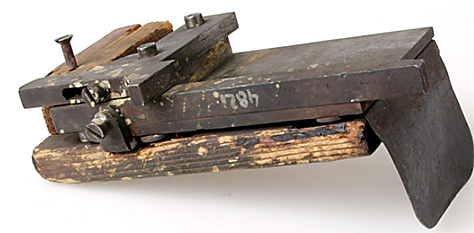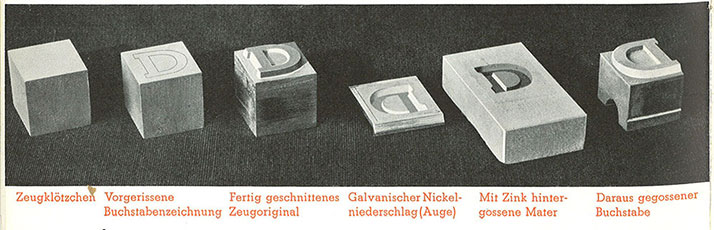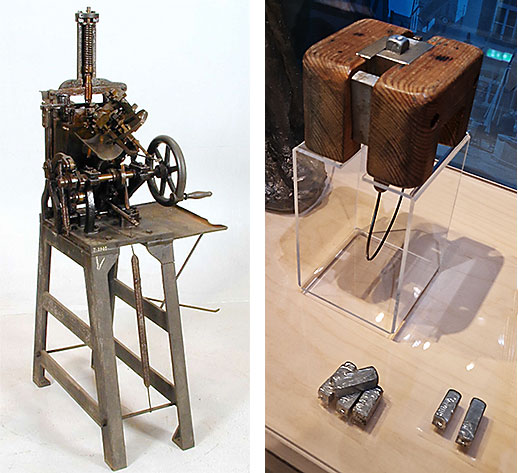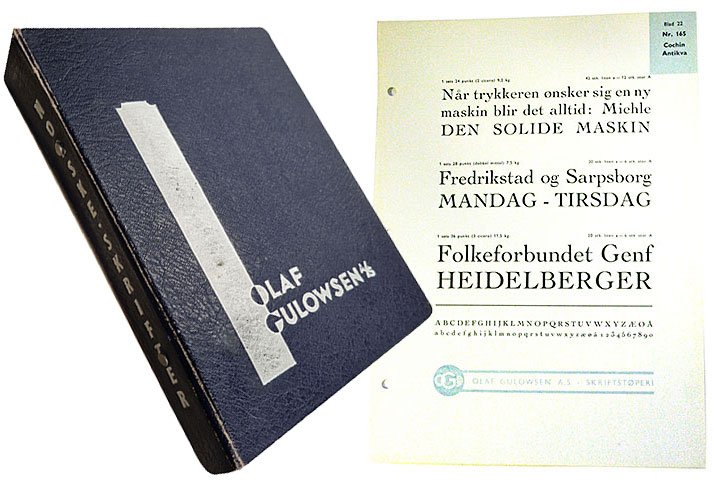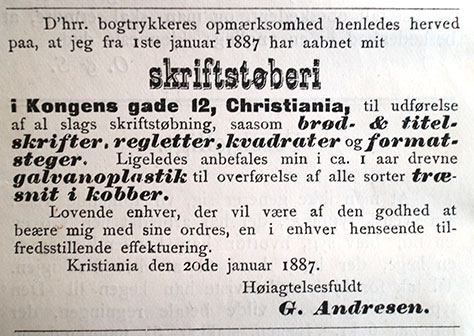
Typografer, grafiske designere og andre med kjærlighet for trykkskrift vil gjenkjenne navn som Stempel, Amsterdam, Klingspor og flere andre som hederskronte skriftstøperier. Disse forsynte norske trykkerier i en årrekke med blyskrift. Men Norge var ikke alltid helt avhengig av import av skrift til sine trykkerier.
For også Norge har en historie innen skriftstøping. Både en kjent, om enn lite omtalt historie om et middels stort norsk skriftstøperi, i tillegg til en ganske ukjent historie om flere mindre skriftstøperier, som her blir fortalt for første gang. Enkelte større trykkerier støpte dessuten noe av sin egen skrift.
Den kjente historien handler om Det norske skriftstøperi i Oslo. Bedriften støpte skrift i 30–40 år på 1900-tallet. Sortimentet var basert på lånte og kjøpte matriser fra Monotype Corporation i England. I 1960 utga firmaet ei bok i anledning sitt 25-års jubileum. Her heter det: «Det hadde til da [bedriftens oppstartsår 1934] ikke eksistert noe skriftstøperi i Norge.»
Dette stemmer ikke. Den nesten ukjente historien om norsk skriftstøping handler om hele seks andre skriftstøperier. Disse var virksomme fra slutten av 1800-tallet og et stykke inn på 1900-tallet, men har vært nær ukjente i vår tid.
Det er ingen holdepunkter for at det ble støpt originale skrifter i disse skriftstøperiene. Å formgi og produsere en original skrifttype var et stort og kostbart arbeid som forutsatte høy fagkunnskap og kunstnerisk talent, i tillegg til et større marked for skriften. Likevel er den norske skriftstøpingen en interessant flik av norsk boktrykkhistorie, som gir et glimt inn i forholdene i boktrykkerfaget da det det var i sterk vekst og tok form for 130 år siden.
Det norske skriftstøperi
Det norske skriftstøperi startet som et skriftstøperi under den grafiske utstyrsleverandøren Olaf Gulowsen A/S i 1934. Det var tilknyttet skrift- og settemaskinprodusenten Monotype i England gjennom deres nordiske sentral for skriftmatriser i Stockholm: Scandinavian Display Matrix Library, som var i virksomhet i hvert fall fram til 2. verdenskrig. I 1950 ble støperiet skilt fra moderfirmaet under eget navn, Det norske skriftstøperi, og hadde i 1960 12 ansatte. Jeg har ikke kunnet fastslå når bedriften opphørte.
I den nevnte jubileumsboka ved firmaets 25-årsjubileum i 1960, Halvor Durban-Hansens Skrift og typer, kan vi lese at uten samarbeidet med Monotype i England ville skriftstøperiet ikke vært mulig å realisere. Men det norske grafiske markedet satte pris på muligheten for omgående levering av skrift fra et innenlands støperi, når kvaliteten var god og prisene konkurransedyktige.
Utvalget av skrift fra Olaf Gulowsen/Det norske skriftstøperi var begrenset, som vist i deres skriftprøve, som av Nasjonalbiblioteket er antatt å være utgitt i 1940. Skriftene ble støpt i grader (størrelser) fra 6 til 72 punkter, men kun Bodoni dekket hele dette spennet. Så å si alle skriftene i prøven lar seg identifisere som Monotype-skrifter.
En brosjyre fra 1950-tallet viser at sortimentet var blitt utvidet noe, bl.a. med de populære bokskriftene Bembo og Goudy, mens andre skrifter var gått ut.
Skriftkatalogen til Olaf Gulowsen A/S fra ca. 1940 (ennå ikke omdøpt til Det norske skriftstøperi). Til høyre en side i katalogen, som viser den den gang populære skriften Cochin. (Ill.: Verkstedet – verkstedet.org)
Skrift og typer er både en vakker og interessant bok, som ikke er vanskelig å skaffe seg antikvarisk i dag. Den gir blant annet en innføring i historien og teknologien knyttet til skriftstøping, som er nyttig å kjenne til i det følgende.
Skriftstøpingens teknikk
Opprinnelig besto framstillingen av typer i å først gravere et såkalt stempel i stål, der bokstaven står i relieff – en såkalt patrise (far-form). Dette stemplet ble så preget inn i et annet og mykere metallstykke, slik at bokstaven sto dyptliggende i dette – en såkalt matrise (mor-form). Fra matrisen støpte man blytypene i et manuelt støpeapparat, en etter en. Før de var klare til bruk, måtte overflødig metall slipes av typene. Et dagsverk kunne resultere i 4000–5000 typer.
Til venstre: en skriftstøper i det 17. århundre, sammen med en kvinne som sliper typene. Til høyre: patrise, matrise og støpeinstrumentet ved håndstøping.
På 1800-tallet ble denne prosessen forbedret på flere måter. Den manuelle håndstøpingen ble fra 1838 avløst av en håndstøpemaskin som økte produktiviteten fire–fem ganger. Etter 1853 kom komplettstøpemaskinen, som støpte typene automatisk, og etter hvert også ferdigstilte dem gjennom sliping og justering. Komplettmaskinen hadde en kapasitet på 6000–10.000 typer i timen, avhengig av skriftgraden på typene.
Framstillingen av matriser – altså originalen i skriftstøpingsmaskinene – ble på sin side først forenklet gjennom oppfinnelsen av galvanoplastikken i 1837. Teknikken gikk ut på å senke patrisen i et elektrolytisk bad. Derved ble det utfelt en avstøpning av den, i nikkel eller kobber, som så kunne brukes som matrise ved støpingen av typene. Neste skritt i den tekniske utviklingen var at det mot slutten av 1800-tallet ble utviklet boremaskiner som framstilte patriser og matriser i metallet, nøyaktig etter tegninger av bokstavene.
Håndstøperen i arbeid. Støpeinstrumentet i venstre hånd, øse for å hente smeltet skriftmetall i høyre. Illustrasjonen ble publisert i en utgivelse fra Bauer skriftstøperi i Tyskland, og vist i Griffin: Type Specimens: A Visual History of Typesetting and Printing.